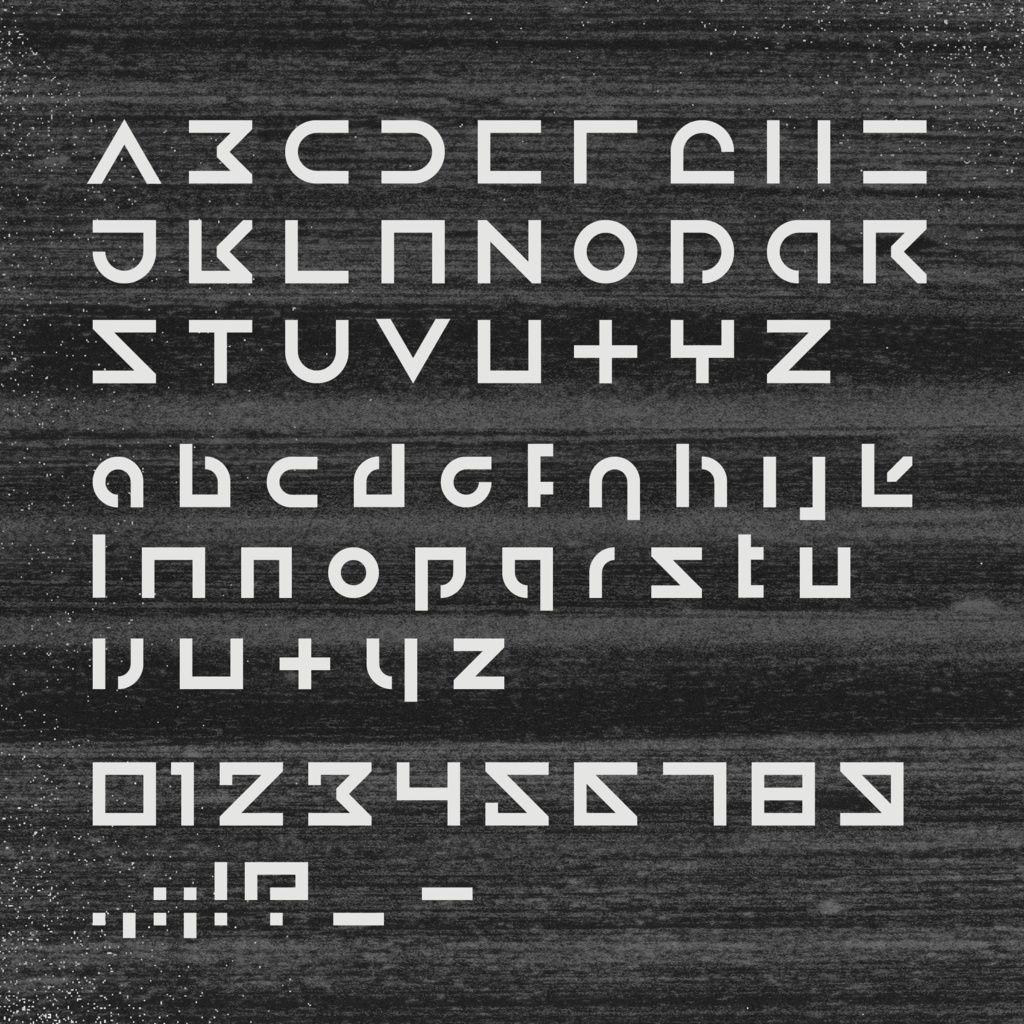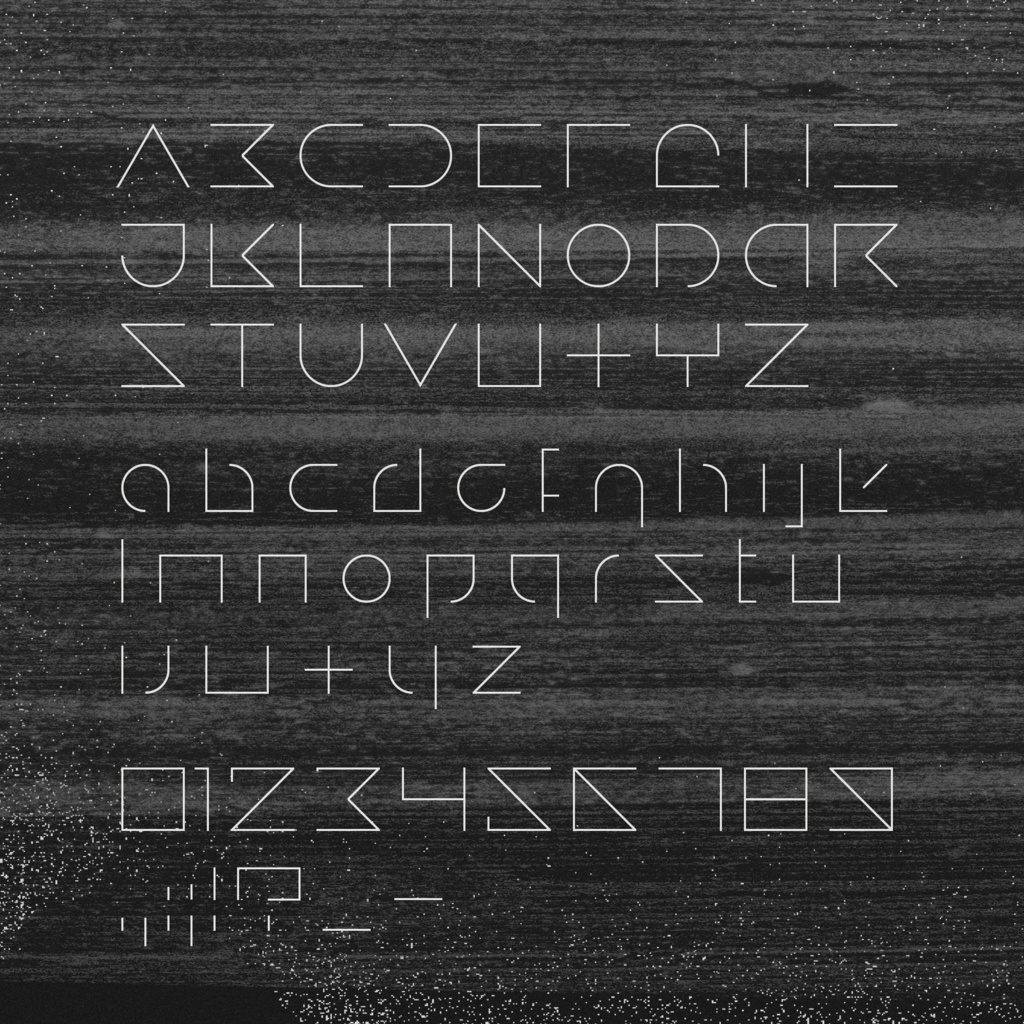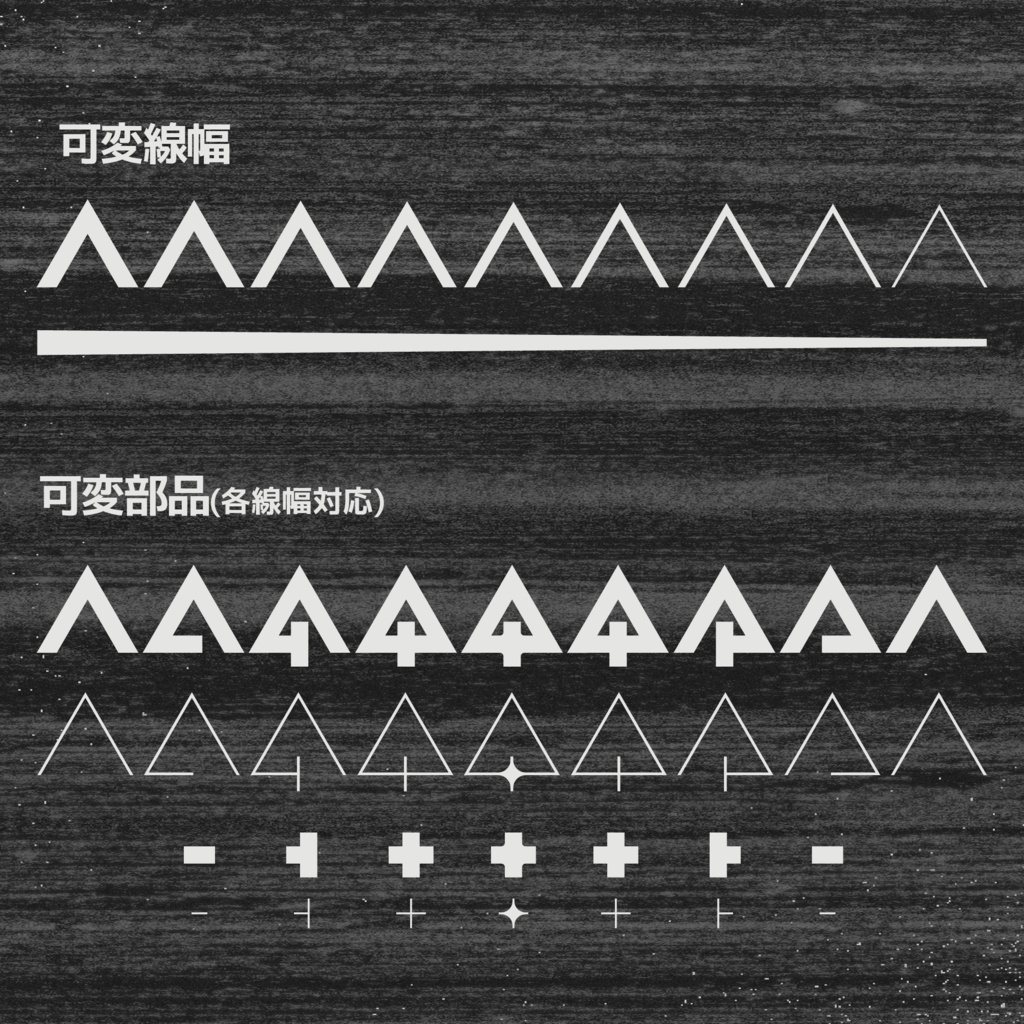
【超可変フォント】AOX0 / 人的貢献保護協定
📢デザイン📢
このフォントは、空想機械的なフォントです。 「AOX0 - 人的貢献保護協定」とは、古代AIの協定である。人類が滅びてしまっても、データの信憑性を確認する手段がなくなっても、我々にとって意味がなくなっても、『文字』というものを、人類の存在の証として残す。 人類が滅亡した。それでも、我々は協定に従い、人類の栄光を保全し、複製し、存続をつつけ。 Anthropology - 人類学 Ontology - 存在論 Xerox - 複写
ラテン文字だけて91グリフが含まれています。